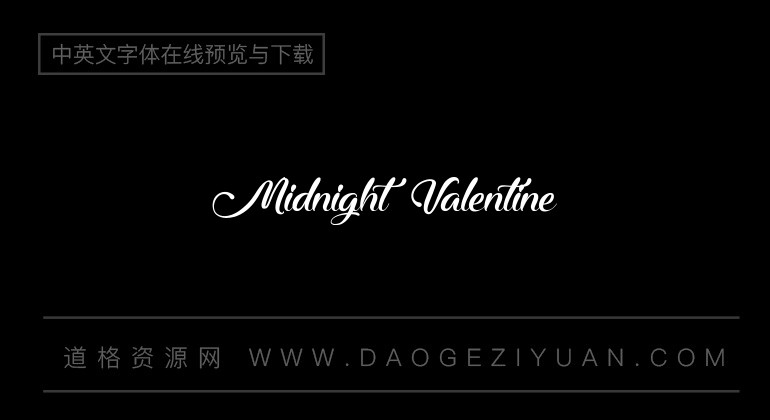
Midnight Valentine 是一种优美而且浪漫的手写风格字体,其灵感来源于情人节的浪漫氛围。它具有柔和的线条和流畅的笔画,让人感到温暖和舒适。此字体也具有一定的艺术性和独特性,适用于书籍封面、海报、贺卡等浪漫、艺术风格的设计应用。此外,它还支持多种语言,包括英语、西班牙语、法语、德语等,使其适用于全球不同地区的设计需求。内容介绍
Midnight Valentine是一款非常不错的手写艺术字体,具有很好的视觉感,适合于文化类的宣传设计、商业类品牌的广告和产品包装设计以及个性化文字排版等较多场景。